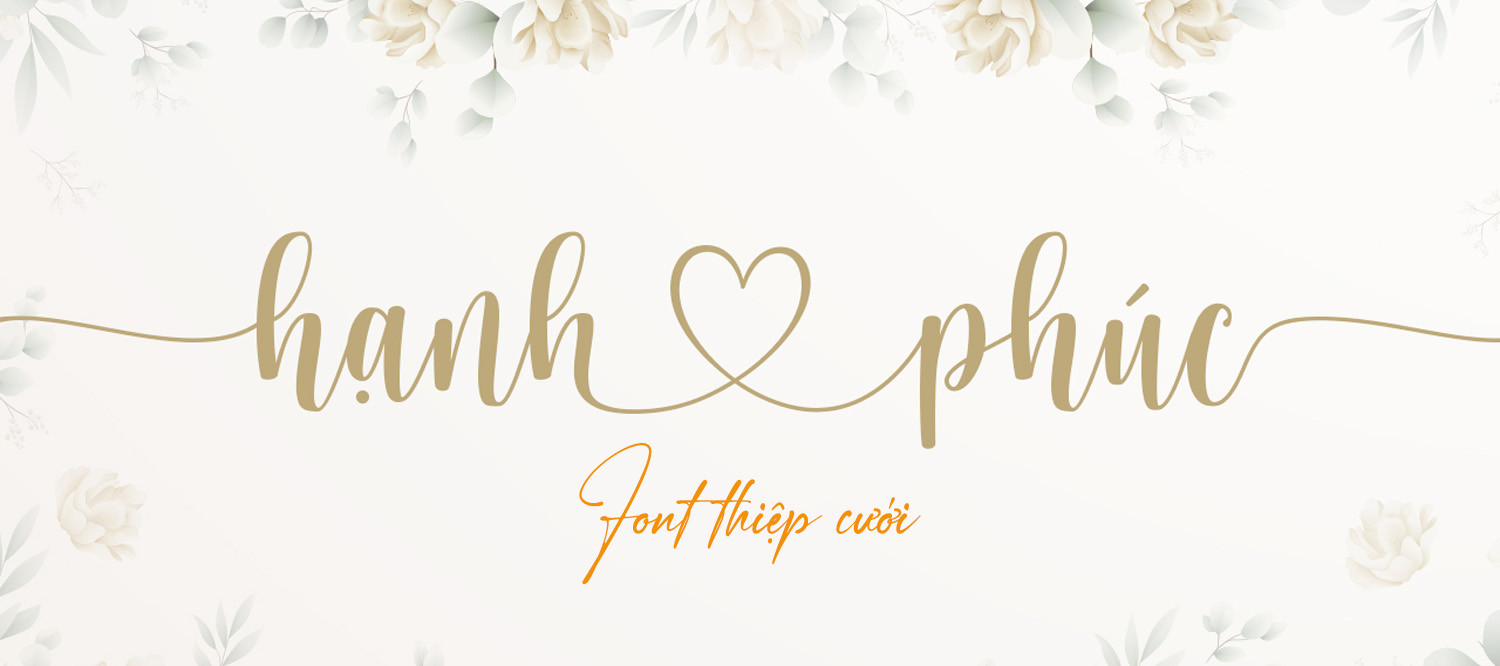
Trang trí thiệp cưới là một phần không thể thiếu trong lễ cưới truyền thống của nhiều nền văn hóa. Điểm nhấn quan trọng của mỗi thiệp cưới chính là font chữ được sử dụng. Font chữ không chỉ mang lại sự trang trọng mà còn góp phần tôn lên vẻ đẹp của bức thiệp. Bài viết này sẽ khám phá các loại font chữ thiệp cưới phổ biến và những lưu ý khi lựa chọn font chữ phù hợp.
Font chữ thiệp cưới không chỉ đơn giản là phần văn bản mà mang theo một số ý nghĩa sâu sắc và tinh tế trong ngày trọng đại của mỗi cặp đôi. Việc lựa chọn font chữ thích hợp là một phần quan trọng không thể thiếu trong việc chuẩn bị cho ngày cưới của bạn.
Font chữ được sử dụng trong thiệp cưới thường phản ánh phong cách và cá tính riêng của các cặp đôi.
Những font chữ cổ điển thường được sử dụng để tăng thêm sự trang trọng và lịch sự cho thiệp cưới.
Các cặp đôi có thể chọn những font chữ mang đậm dấu ấn riêng của họ.
Font chữ không chỉ là văn bản mà còn là một phần của nghệ thuật trên thiệp cưới.
Font chữ trong thiệp cưới cũng truyền tải những thông điệp và cảm xúc đặc biệt từ các cặp đôi đến khách mời.
Chọn font chữ thiệp cưới đóng vai trò quan trọng không chỉ trong việc truyền tải thông điệp mà còn là yếu tố quyết định thẩm mỹ của mỗi bức thiệp. Dưới đây là một số font chữ được ưa chuộng sử dụng trong ngày trọng đại hiện nay:
Font chữ ký TH Corinthiago Việt hóa mang đậm tính nghệ thuật và lãng mạn, thích hợp cho việc viết thiệp cưới. Với các nét chữ mềm mại và tinh tế, nó tạo nên sự trang nhã và đẳng cấp cho những lời chúc hay trong dịp đặc biệt này. Đường nét mượt mà của font chữ ký này không chỉ làm nổi bật những thông điệp yêu thương mà còn là điểm nhấn thẩm mỹ cho thiệp cưới, phản ánh sự quý phái và chuyên nghiệp trong từng chi tiết thiết kế.
Font chữ ký SVN-Janelotus rất phù hợp để sử dụng trong thiết kế thiệp cưới. Với phong cách mềm mại, thanh thoát và đặc biệt là sự tinh tế của từng nét chữ, font này có thể mang đến một cái nhìn độc đáo và sang trọng cho thiệp cưới.
Khi áp dụng font SVN-Janelotus vào thiết kế thiệp cưới, bạn có thể tạo ra những bức thiệp mang tính cá nhân cao, với chữ ký mang đậm dấu ấn riêng của đôi bạn. Đặc biệt, sự mượt mà và thân thiện của font này sẽ làm cho các từ và câu thơ trên thiệp cưới trở nên ấn tượng và dễ đọc hơn.
Font SVN-Darleston Việt hóa là sự lựa chọn lý tưởng cho việc thiết kế thiệp cưới nhờ vào sự kết hợp độc đáo giữa phong cách viết tay và nét chữ nghiêng tinh tế. Với những đường nét tự nhiên và gần gũi, font chữ này mang đến sự ấm áp và cá nhân hóa cho mỗi chi tiết trên thiệp.
Sự dễ đọc và tính thẩm mỹ của SVN-Darleston cũng làm nổi bật các thông điệp lãng mạn và chân thành trong lời chúc từ những người thân yêu. Sẽ thật đặc biệt khi sử dụng font này để tạo ra những bản thiệp cưới độc đáo, phản ánh đẹp và tinh tế của ngày trọng đại đầy ý nghĩa.
Font chữ TH Frenchasette Việt hóa là sự kết hợp tinh tế giữa sự cổ điển và hiện đại, thích hợp cho thiết kế thiệp cưới mang phong cách thanh lịch và lãng mạn. Với các nét chữ mềm mại và đường cong tinh tế, font này mang đến cảm giác ấm áp và lãng mạn, thích hợp cho các thiệp cưới với phong cách truyền thống nhưng vẫn mang đậm tính cá nhân.
Sự hòa quyện giữa những nét chữ thư pháp và sự đơn giản của hiện đại tạo nên sự sang trọng nhẹ nhàng, làm nổi bật những thông điệp tình yêu và lời chúc hạnh phúc trong ngày trọng đại này.
Font chữ viết tay Việt hoá cho thiệp cưới TH Signatura mang đậm nét thanh lịch và sang trọng. Với đường nét mềm mại và cách bố trí tinh tế, nó thường được sử dụng để tạo nên sự ấm cúng và lãng mạn trong các thiệp cưới. Đặc điểm chủ yếu của TH Signatura là sự tinh tế và độc đáo, phù hợp để thể hiện tình cảm trang trọng và lời chúc tốt đẹp nhất đến với đôi uyên ương.
Font chữ Maistoray là một lựa chọn tuyệt vời cho thiệp cưới nhờ vào sự đẹp mắt và tính biểu cảm đặc trưng của nó. Với những đường nét uốn lượn tinh tế và sự điều chỉnh tỷ lệ hài hòa, Maistoray tạo nên sự sang trọng và độc đáo cho mọi thiệp cưới. Sự độc đáo của font chữ này không chỉ nằm ở cách thể hiện chữ ký mà còn ở cảm giác mượt mà khi nhìn vào từng chữ cái và từng dòng chữ. Với Maistoray, thiệp cưới của bạn sẽ trở nên đặc biệt và thu hút từ cái nhìn đầu tiên.
Font chữ viết tay Việt hoá TH Dellyani là một lựa chọn lãng mạn và tinh tế cho thiết kế thiệp cưới. Với nét viết tay truyền thống nhẹ nhàng và chữ cái được thiết kế cân đối, TH Dellyani mang lại sự sang trọng và độc đáo cho bất kỳ thiệp cưới nào.
Đặc biệt, với sự mềm mại và khả năng đọc dễ dàng, font này không chỉ thu hút mà còn làm nổi bật những lời chúc ngọt ngào và thông điệp tình yêu trên thiệp cưới. Sự tỉ mỉ và sự tinh tế trong từng nét chữ của TH Dellyani sẽ làm cho mỗi thiệp cưới trở nên đặc biệt và đáng nhớ.
Font SVN-Pateglamt Script là một font chữ ký mềm mại và đầy sáng tạo, với những nét viết cong và nổi bật. Nó mang đến cảm giác của một chữ ký cá nhân, mang tính chất cá nhân hóa cao. Điểm nổi bật của font này là sự tinh tế trong từng nét chữ, tạo nên sự dịu dàng và lôi cuốn. Với thiết kế tự nhiên và mượt mà, SVN-Pateglamt Script thường được sử dụng trong các thiết kế có yêu cầu về tính cá nhân và sự độc đáo.
Như vậy, font chữ không chỉ đơn giản là một phần văn bản trên thiệp cưới mà nó còn mang đến một giá trị sâu sắc hơn, từ việc thể hiện phong cách và cảm xúc cho đến việc tạo sự thống nhất và nâng cao giá trị thẩm mỹ. Hy vọng bài viết của S99.VN giúp bạn lựa chọn được font chữ thiệp cưới phù hợp để tạo ra những thiệp cưới không chỉ đẹp mắt mà còn đầy ý nghĩa và có cá tính riêng.